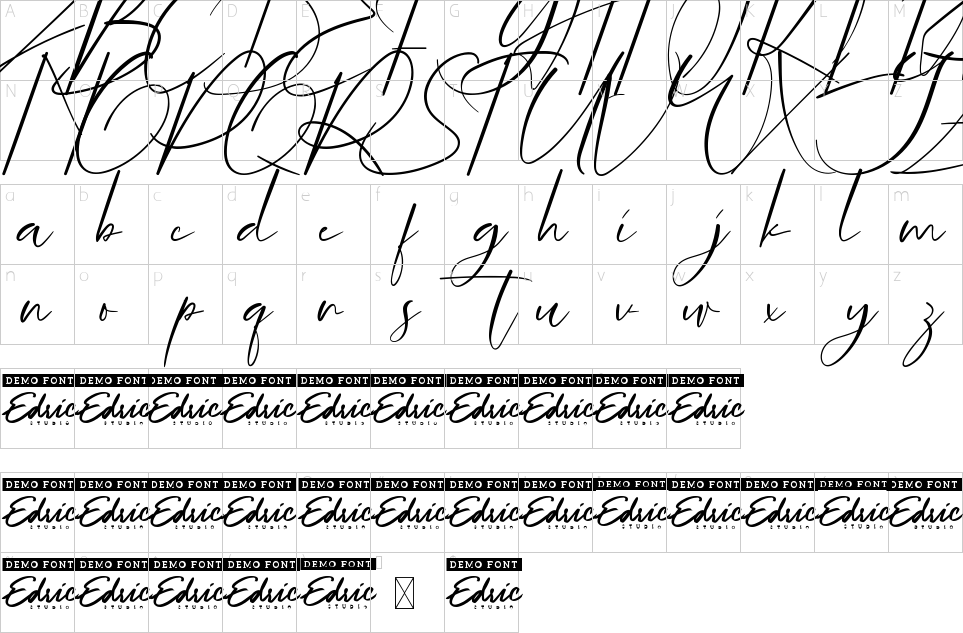
A Pramusita é uma fonte elegante e versátil, projetada pelo EdricStudio. Suas linhas finas e detalhes suaves criam um estilo moderno e sofisticado. Ideal para editoriais de revistas, design gráfico e qualquer projeto que valoriza uma aparência limpa e profissional. Esta fonte foi projetada para funcionar de maneira ótima tanto no Windows quanto no Mac. Com apenas 430 downloads, a Pramusita é uma fonte gratuita e única que pode enriquecer seu trabalho. Fornecida de forma gratuita, a Pramusita é uma opção perfeita para qualquer designer que busca um look moderno e elegante para seus projetos.